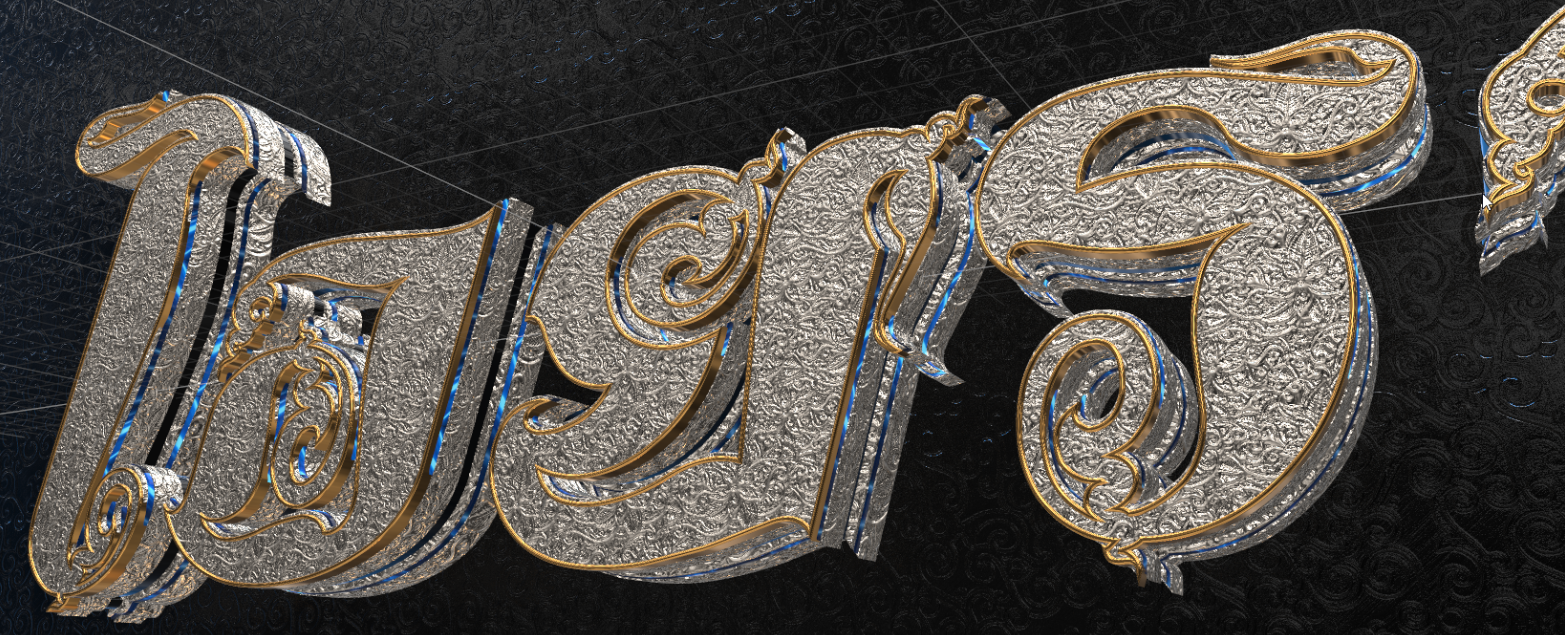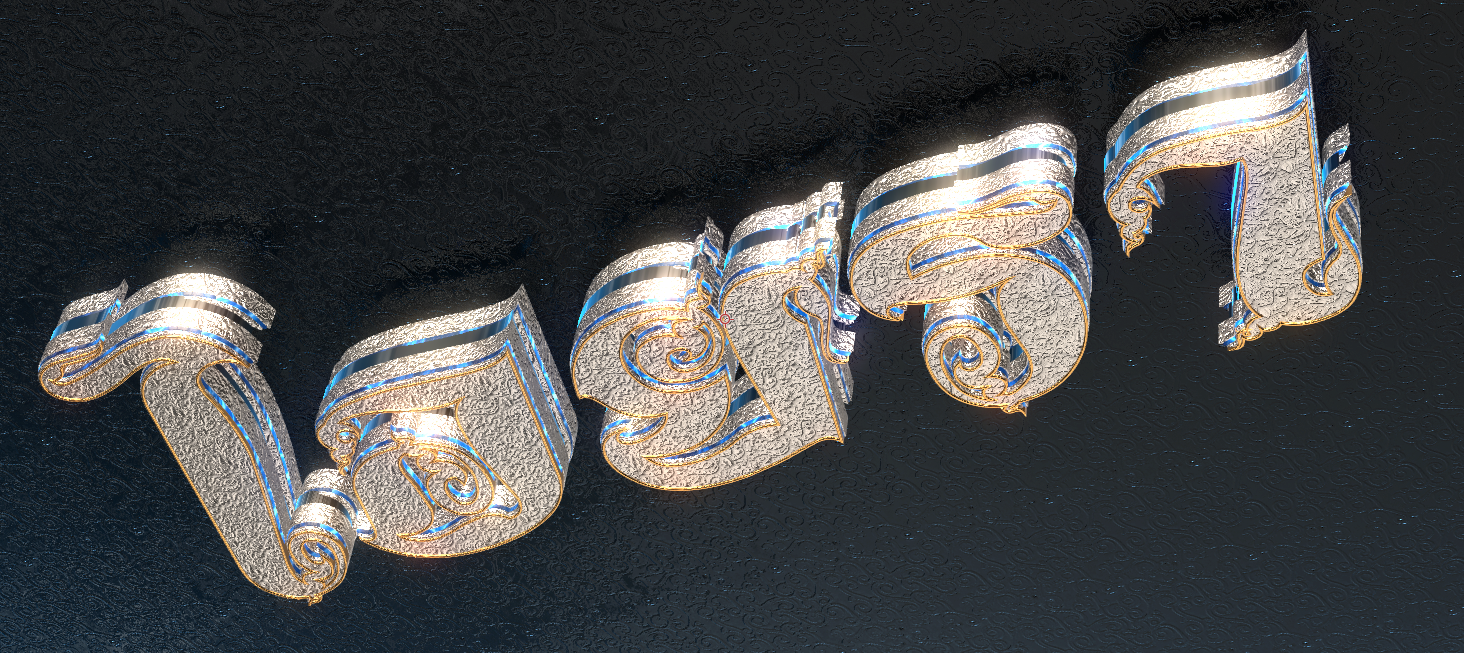
PKDSTUDIO
ชานมฟอนต์ (PKD CHANOM)
ฟอนต์ลายมือน่ารัก สดใส เป็นกันเอง เหมาะสำหรับงานคอนเทนต์ โพสต์โซเชียล สติกเกอร์ คาเฟ่ และงานออกแบบทั่วไป
• มีตัวอักษรโปร่งผสมในบางตำแหน่ง
• ได้รับฟอนต์ครบทั้ง 3 น้ำหนัก (บาง / ปกติ / หนา)
• ไม่มีตัวอักษรโปร่งผสม
• รองรับภาษาไทย ภาษาอังกฤษ ตัวเลข และสัญลักษณ์
TCHA STUDIO 23
ฟอนต์ตำไทย (TCS4TumThai)
ปลดล็อกเวอร์ชั่นเต็ม ได้ตัวหนังสือปกติไม่ผสมตัวโปร่ง
แฟ้มฟอนต์
แฟ้มฟอนต์คุชชั่น (FFCushion) โหลดฟรีไฟล์ Demo
พิกัดฟอนต์
พิกัดฟอนต์ดิซซี่ (PKF-dizzy)
ฟอนต์ตัวเหลี่ยม เป็นระเบียบ
- ฟอนต์ FkBerry ฟอนต์ลายมือแนววัยรุ่น เส้นแบนปลายตัด ตัวอวบอ้วนน่ารักค่ะ
SP_Aiyara ไอยรา
SP_Aiyara ไอยรา เป็นฟอนต์ที่อยู่ในโครงการอักษราสูตรไทยวิจิตร มุ่งเน้นการออกแบบลายเส้นให้กลมกลืนกับศิลปะลวดลายไทย
จัดรูปแบบอักษรให้เป็นเอกลักษณะเฉพาะตัว เข้ากันกับชุดอักษรนั้นๆ รวมถึงอักษรภาษาอังกฤษและสัญลักษณ์อื่นๆครบถ้วนบริบูรณ์
พร้อมใส่ฟีเจอร์ (แก้สระลอย-ล็อกเป้าเข้าพิกัด) เพื่อความสวยงามและลงตัว ไม่ว่าจะเป็นช่องไฟ สระวรรณยุกต์ ชั้นล่างชั้นบน
และแยกนิคหิตเพื่อการใช้พิมพ์ภาษาบาลีไห้ถูกต้องตามหลักไวยากรณ์ ภายในฟอนต์ๆเดียว (Microsoft-Adobe ต้องเปิดค่ารองรับ)
ฟอนต์อักษรวิจตรชุดนี้ เหมาะสำหรับงานออกแบบเฉพาะด้าน เช่น โลโก้ ป้ายชื่อ สิ่งพิมพ์ โฆษณา งานเทศกาลพิเศษอื่นๆ เป็นอาทิ
ทั้งนี้ยังมีพรีเซนต์ข้อความสไตล์เอฟเฟค ในรูปแบบต่างๆเล็กน้อย เพื่อเป็นแนวทางในการใช้งานฟอนต์ ของผู้สนใจทั่วไปด้วย